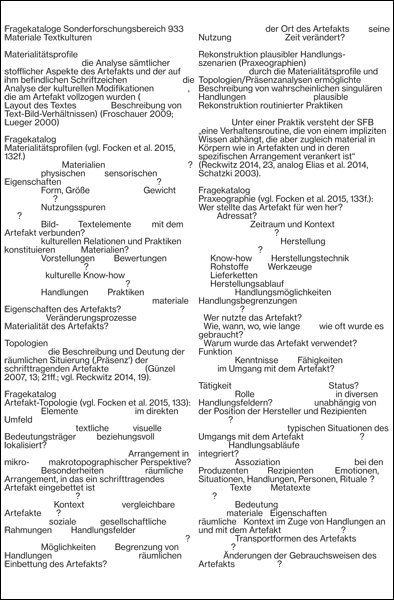
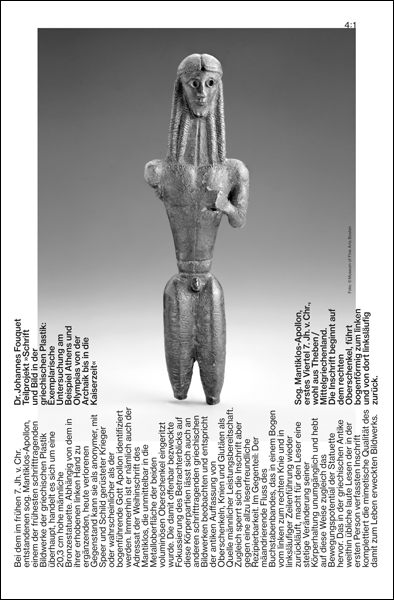
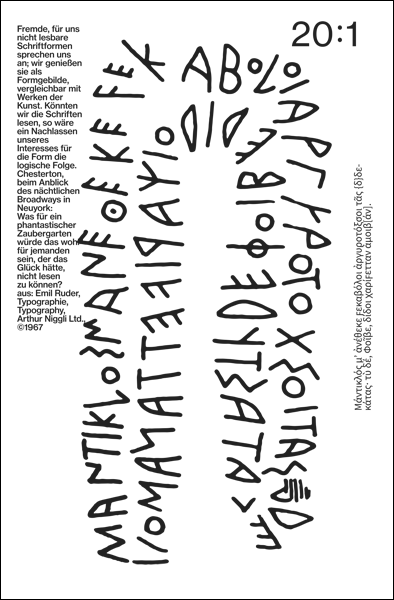
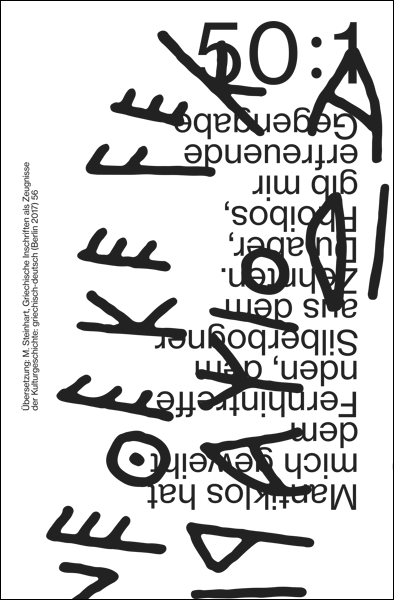
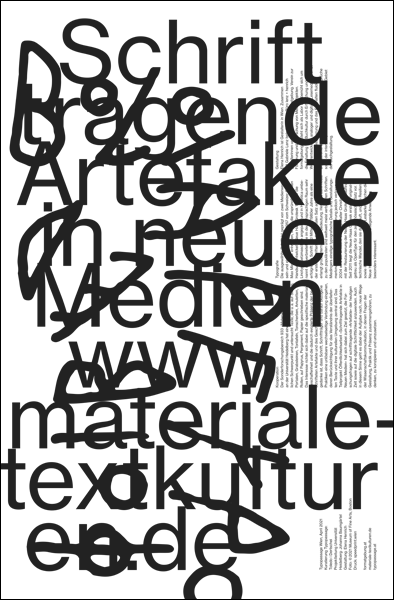
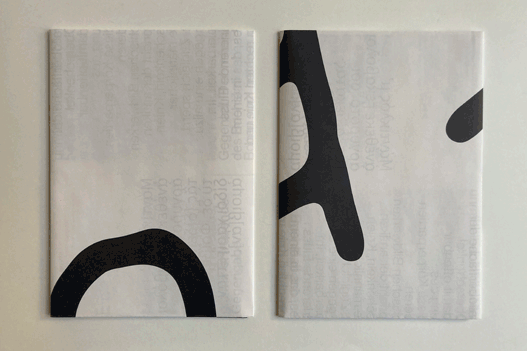
Der Sonderforschungsbereich 933 Materiale Textkulturen an der Universität Heidelberg hat einen altertumswissenschaftlichen Schwerpunkt und untersucht Texte, die u. a. auf Säulen, Portalen, Grabsteinen, Tontafeln, Tonscherben, Amuletten, Rollen, auf Papyrus, Pergament, Papier geschrieben sind. Das Interesse richtet sich dabei auf die spezifische materiale Beschaffenheit und die dadurch evozierte Präsenz der beschrifteten Artefakte und des Geschriebenen selbst. Der Leitgedanke ist, dass Schrift, Schriftträger und darauf bezogene Praktiken eine unlösbare wechselseitige Verbindung eingehen, deren Berücksichtigung für das Verständnis der überlieferten Texte und ihrer kulturellen Umgebung zentral sind. Das Teilprojekt Öffentlichkeitsarbeit »Schrifttragende Artefakte in Neuen Medien« hat sich dabei zum Ziel gesetzt, die Forschungsfragen auf schrifttragende »Artefakte« der heutigen Zeit sowie auf die digitale Schriftlichkeit anzuwenden. Auch in diesem Sinne geht es dabei der Aufgabe nach, neue Wege der Wissenschaftskommunikation, in denen Fragen der Gestaltung, Praktik und Präsenz zusammengehören, zu denken, zu konzipieren und umzusetzen. [siehe Kooperation II]
Typografie
Die ausgewählte Schrift ist geprägt von zwei Medienwechseln und einer Restaurierung: 1957 vom Schweizer Grafiker Max Miedinger entworfen, wurde die ursprünglich für den Handsatz entwickelte Neue Haas Grotesk 1959 für die Linotype-Setzmaschine angepasst und in Helvetica umbenannt und verbreitet. Die im deutschsprachigen Raum sehr erfolgreiche Schrift wird Mitte der 1980er Jahre als eine der ersten Schriften für den digitalen Satz adaptiert und erlangt große internationale Bedeutung. Helvetica zählt heute zu den populärsten und weltweit meist verbreiteten Schriften. Miedingers einstige typografische Details und Gestaltungsmerkmale gingen bei der Digitalisierung jedoch verloren. 2004 wird der britische Schriftgestalter Christian Schwartz mit der Restaurierung der Neuen Haas Grotesk beauftragt. Seit 2011 liegt die Neue Haas Grotesk erstmals originalgetreu als OpenType für den zeitgenössischen Satz vor. Der technische Wandel, den sie durchläuft, und ihre Resilienz sowie ihre klare Gestalt und gute Lesbarkeit machen die Neue Haas Grotesk für die vorliegende Anwendung besonders interessant.